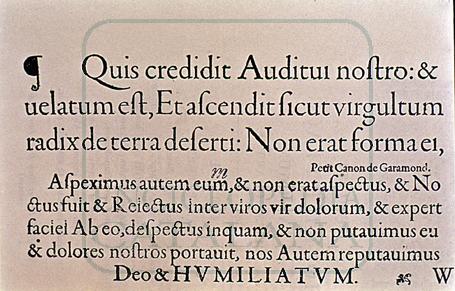
Jacques (Jakob) Sabon
Kann mir vielleicht jemand helfen? Ich benötige ein "a" in irgendeiner Form von Jacques Sabon (Schüler Claude Garamonds, Angestellter in der Schriftgießerei Christoph Plantins und Produzent von Schriften von Robert Granjon). Leider finde ich nur die Sabon von Jan Tschichold, aber keinen ursprünglichen Buchstaben. Vielleicht hat jemand einen originalen Druck von ihm oder eine Kopie oder Foto einer gedruckten Seite oder sonst irgend etwas?
Sabon arbeit bei Christoffel Plantijn war wohl eher eine Episode, wichtiger war, dass er nach Frankfurt ging und dort in der Officin von Christian Egenolff arbeitete, die er nach Egenolffs Tod erfolgreich weiter führte (später Egenolff-Sabon-Berner-Lutherische Gießerei). Besonders wichtig war, dass er einige Garamond-Typen* im Gepäck hatte, die auch in Frankfurt weiter benutzt wurden. Eine Schriftprobe dieses Hauses wurde so zur Vorlage einiger wichtiger heutiger Garamond-Varianten, etwa Slimbachs Adobe-Garamond, die Stempel-Garamond und Tschicholds Sabon (andere Varianten, z.B. Original Garamond und Garamond Simonicini, leiten sich aus Jean Jannons barocker Überarbeitung für die Imprimerie Nationale ab).
Wenn Du es genau machen willst, müsstest Du also in Bibliothekskatalogen nach Drucken und Faksimiles aus Frankfurt so ab 1560 suchen.
Ansonsten findet sich das berühmte Schriftmuster auch (in sparsamer Qualität) im Web:
* einige Schreiben die Schriften eher Garamonds Lehrer Antoine Augereau (um 1485-1534) zu, Garamond habe sie demnach lediglich nachgeschnitten. Derzeit ist keine der beiden Thesen beweisbar.
Auf dieser Seite findest Du ein Beispiel von gebrochener Schrift aus der Zeit und der Egenolff-Gießerei. Keine Ahnung, ob Sabon an diesen Lettern mitwirkte.